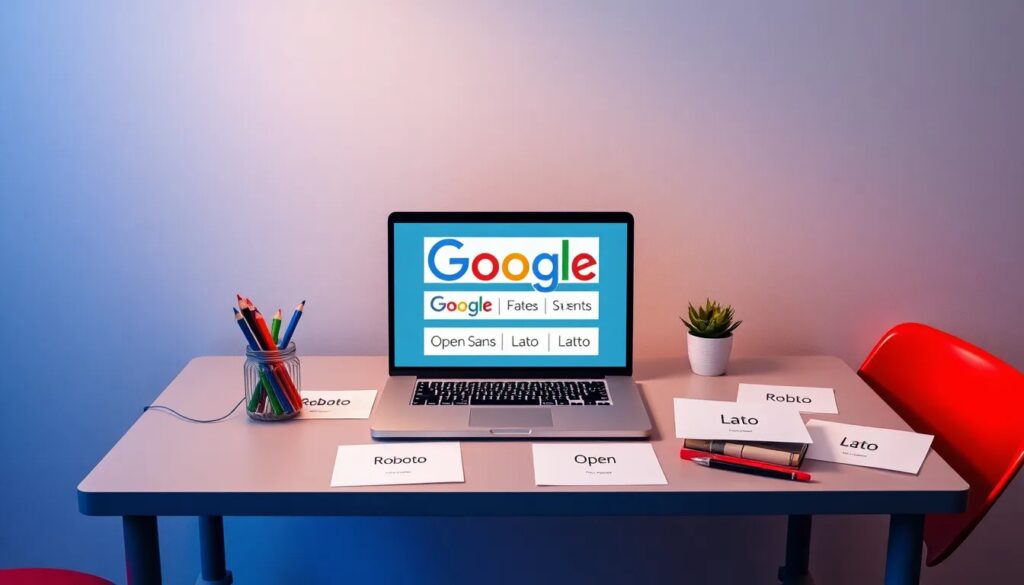
Tipografía de Google: Guía completa para su uso
Tipografía de Google: La guía definitiva para su uso
La tipografía de Google se ha convertido en una herramienta esencial para diseñadores y desarrolladores web. Con más de 1,400 fuentes gratuitas, Google Fonts permite personalizar cualquier sitio web de manera sencilla y efectiva. En este artículo, exploraremos todo lo relacionado con Google Fonts, desde su importancia hasta cómo integrarlas correctamente en tus proyectos.
¿Qué es la tipografía de Google y por qué es importante?
La tipografía de Google es un conjunto de fuentes tipográficas que están disponibles de forma gratuita para su uso en proyectos web. Esta colección no solo mejora la estética de los sitios, sino que también optimiza la experiencia del usuario y el rendimiento SEO.
Su importancia radica en que permite a los diseñadores web elegir tipografías que se adapten a la identidad visual de su marca, logrando así una comunicación más efectiva con el usuario. Además, todas las fuentes son optimizadas para la web, lo que significa que están diseñadas para cargarse rápidamente y verse bien en diferentes dispositivos y navegadores.
Utilizar la tipografía de Google puede mejorar la legibilidad y la accesibilidad de tu contenido, lo que resulta en una mejor experiencia de usuario y una mayor retención de visitantes. En un mundo digital donde la primera impresión cuenta, elegir la tipografía adecuada es crucial.
¿Cómo seleccionar fuentes en Google Fonts?
Seleccionar una fuente en Google Fonts puede parecer abrumador debido a la gran variedad disponible. Sin embargo, hay algunos pasos que puedes seguir para facilitar el proceso.
- Define el estilo: Antes de buscar, ten claro el estilo que deseas reflejar en tu sitio, ya sea moderno, clásico o minimalista.
- Usa filtros: Google Fonts ofrece filtros para que puedas buscar por categoría, como serif, sans-serif, display, y handwriting.
- Prueba antes de elegir: Google Fonts permite previsualizar cómo se verán las fuentes en tu texto, lo que es muy útil para tomar decisiones.
- Consulta la popularidad: Las fuentes más populares a menudo tienen una mejor legibilidad y están más probadas en términos de uso.
Recuerda que la tipografía de Google no solo se trata de estética, sino también de funcionalidad. Asegúrate de que la fuente que elijas se mantenga legible en diferentes tamaños y dispositivos.
¿Cuáles son las ventajas de utilizar Google Fonts para diseñadores web?
Usar Google Fonts ofrece múltiples ventajas para los diseñadores web. Aquí te mencionamos algunas de las más destacadas:
- Variedad y flexibilidad: Con más de 1,400 fuentes, elige entre una amplia gama de estilos y diseños que se adapten a tus necesidades.
- Optimización SEO: Las fuentes de Google están optimizadas para la web, lo que puede mejorar la velocidad de carga de tu página.
- Compatibilidad: Las fuentes son compatibles con todos los navegadores principales, evitando problemas de visualización.
- Fácil integración: Se pueden integrar fácilmente mediante CSS, lo que ahorra tiempo en el proceso de diseño.
- Actualizaciones constantes: Google mantiene y actualiza su colección de fuentes, asegurando que siempre tendrás acceso a las últimas tendencias.
Estas ventajas hacen que la tipografía de Google sea una opción preferida entre los diseñadores, facilitando la creación de sitios web atractivos y funcionales.
¿Qué tipografías destacan en Google Fonts?
Entre la vasta colección de Google Fonts, hay algunas tipografías que se destacan por su popularidad y usabilidad. Aquí te mencionamos algunas de las más recomendadas:
- Roboto: Moderna y versátil, ideal para interfaces y lectura en pantallas.
- Open Sans: Muy legible, perfecta para textos largos y sitios corporativos.
- Lato: Con un diseño elegante, es excelente para sitios creativos y de moda.
- Montserrat: Popular por su estilo urbano y moderno, ideal para encabezados.
- Oswald: Una fuente condensada que es perfecta para títulos y encabezados llamativos.
Estas fuentes no solo son populares entre los diseñadores, sino que también mejoran la experiencia de usuario al ser altamente legibles en diferentes dispositivos.
¿Cómo integrar Google Fonts en tu proyecto de diseño web?
Integrar Google Fonts en tu sitio web es un proceso sencillo que puede realizarse en pocos pasos. A continuación, te mostramos cómo hacerlo:
Primero, accede a Google Fonts y selecciona la o las fuentes que deseas utilizar. Después de seleccionar, haz clic en el botón "Select this style".
Una vez seleccionadas las fuentes, verás una ventana con un código que puedes copiar. Este código incluirá un enlace que debes colocar en la sección <head> de tu HTML.
Por último, utiliza CSS para aplicar la fuente a los elementos deseados de tu sitio. Por ejemplo:
body {
font-family: 'Roboto', sans-serif;
}
Esta integración no solo es funcional, sino que también ayuda a mantener una coherencia visual en todo tu proyecto.
¿Cuáles son las mejores prácticas para usar Google Fonts?
Para maximizar el rendimiento y la eficacia de Google Fonts en tus proyectos, aquí te dejamos algunas mejores prácticas:
- Limita el número de fuentes: Usar demasiadas fuentes puede hacer que tu sitio se vea desordenado y afectar la velocidad de carga.
- Carga asíncrona: Implementa técnicas de carga asíncrona para mejorar la velocidad de carga de tu sitio.
- Planifica el uso de estilos: Define claramente qué estilos necesitas (negritas, cursivas) para evitar cargas innecesarias.
- Prueba en diferentes dispositivos: Asegúrate de que las fuentes se vean bien en móviles y tabletas.
Siguiendo estas recomendaciones, podrás utilizar la tipografía de Google de forma eficiente, asegurando un mejor rendimiento de tu sitio web.
¿Cómo optimizar la velocidad de carga con Google Fonts?
La velocidad de carga es un factor esencial para la experiencia del usuario y el SEO. Aquí te ofrecemos algunas estrategias para optimizar la velocidad de carga al usar Google Fonts:
- Minimiza las fuentes: Selecciona solo las variantes que realmente necesitas para evitar cargas innecesarias.
- Utiliza subsets: Al cargar fuentes, considera usar subsets para limitar el número de caracteres especializados.
- Implementa la carga asíncrona: Cargar las fuentes de forma asíncrona evitará que bloqueen la renderización de la página.
- Almacena en caché: Configura la caché de tu navegador para mejorar la velocidad de carga en visitas repetidas.
Aplicando estas técnicas, garantizarás una experiencia más fluida para tus usuarios, lo que puede traducirse en un menor porcentaje de rebote y una mejor retención de visitantes.
Explorar la tipografía de Google puede no solo mejorar la apariencia de tu sitio web, sino también optimizar su rendimiento y funcionalidad. Ya sea que busques una fuente elegante o una solución práctica, Google Fonts tiene lo que necesitas.